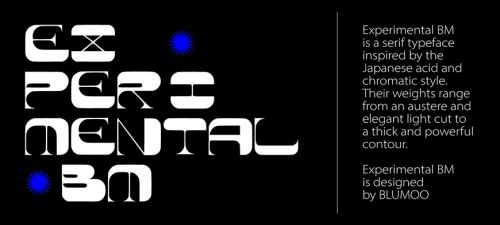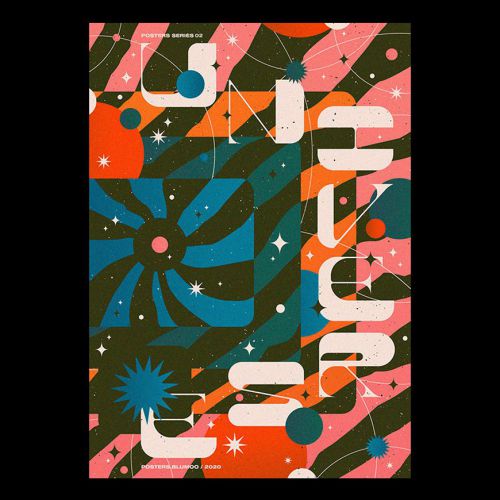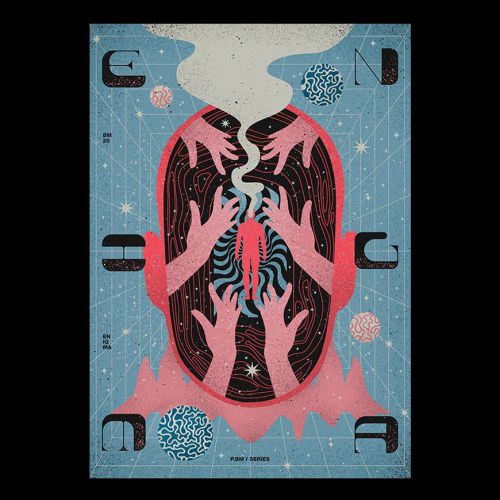
Experimental Bm
### Experimental Bm:创意英文Display字体,释放设计趣味 Experimental Bm是一款充满个性的英文(拉丁)Display字体,以“有趣”为核心设计理念,为创意场景注入鲜活表现力。字体字形修长舒展,重心稳定居中,中宫设计适中,既保留了字符间的空间呼吸感,又让排版整体紧凑有序,视觉平衡感突出。 Experimental Bm在笔型设计上独具巧思:方头笔画搭配利落斜切处理,局部笔画采用“断开”结构,打破传统字体的规整框架,赋予字符灵动跳脱的视觉节奏。字重饱满粗壮,笔画粗细均匀,确保在标题、海报等大尺寸应用中展现强烈冲击力,细节处的斜切棱角则增添设计温度,让文字成为画面中的趣味焦点。 作为免费商用字体,Experimental Bm适配常规字符集,适用于品牌标识、创意海报、社交媒体标题、潮流文创等多元场景。无论是传递年轻活力的品牌调性,还是打造吸睛的视觉焦点,这款字体都能以独特设计语言,助力设计师轻松实现创意表达。